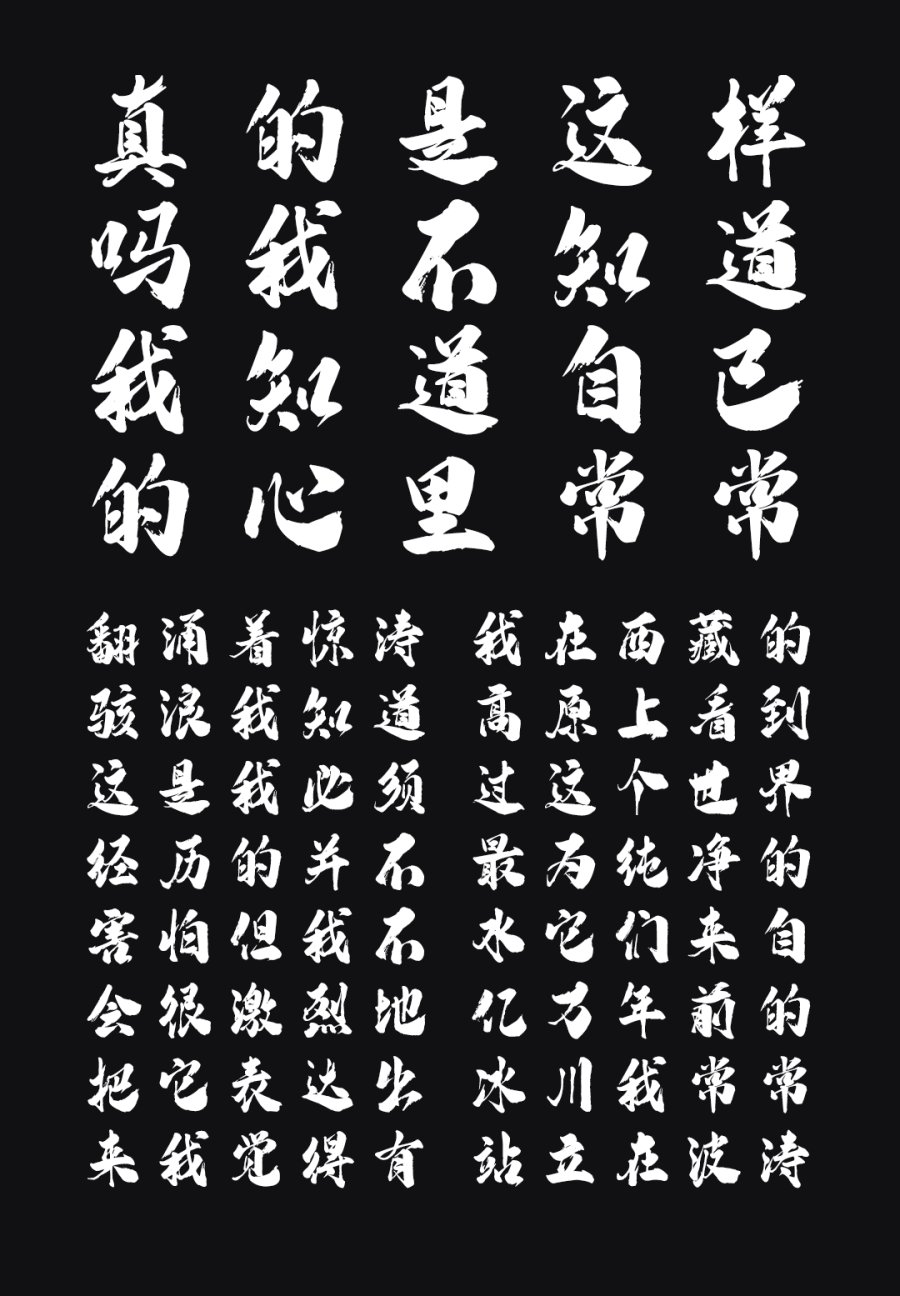
汉标高清锐毛字体是一款具有书法味道的纯手写字体,作者运用大号毛笔精心书写,楷书味道浓厚,由于字体较大,使得笔画清晰度较高,笔画中也减少了过多的处理和笔势,厚重、饱满。因为是纯手写的原因,它独特的气质更与其他字体不同,看似统一,其实各有各的味道,每个字都可以独具风情。
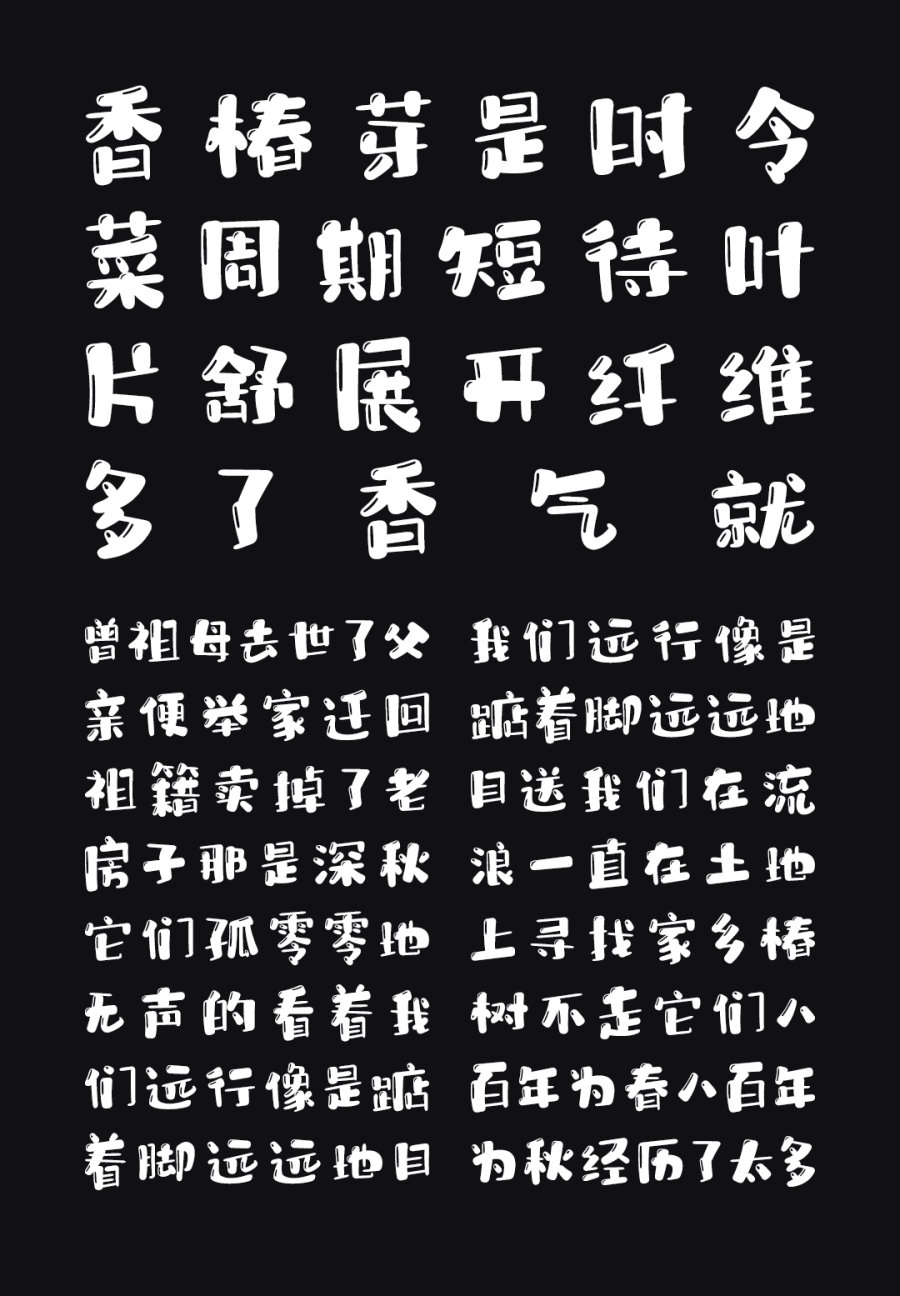
华光布小兜体是一款创意卡通字体。可以使文字排版内容活泼可爱、充满个性。字体风格充满童趣,带弧度的竖笔和具有大弯度的笔画设计能够营造出活泼顽皮且带手写意味的风格。高光的点缀使整个字体饱满立体,笔画风格及其可爱,圆润中透着可爱,让人爱不释手。